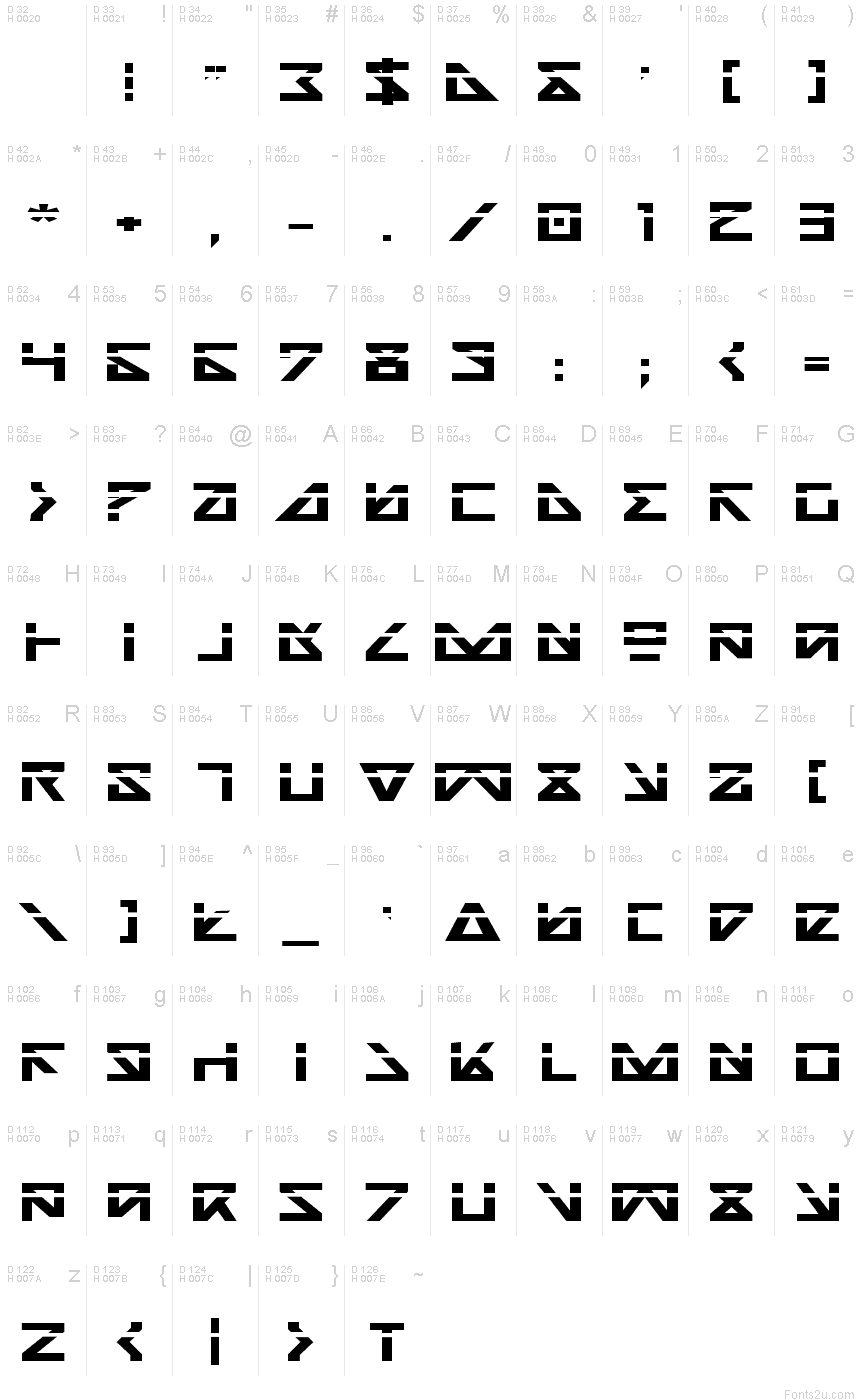
Nick Turbo Bold ExpLaser od Iconian Fonts to darmowy krój displayowy w stylu techno, o ostrym, arcade'owym charakterze. Litery zbudowane są z szerokich czarnych bloków przeciętych ostrymi przekątnymi, co nadaje alfabetowi szybki, mechaniczny rytm, bardziej przypominający grafikę na deskach rozdzielczych czy logotypy sci-fi niż zwykłe liternictwo.
Świetnie sprawdza się w tytułach gier, nagłówkach plakatów, okładkach albumów, miniaturach streamingowych i grafikach eventowych, gdzie potrzeba natychmiastowego efektu syntetycznej szybkości. Ponieważ wielkie litery są zwarte i kanciaste, font ten pasuje również do krótkich kart tytułowych, logotypów i monogramów, które zyskują na jego „spawanym”, maszynowym wyglądzie.
Nick Turbo Bold ExpLaser